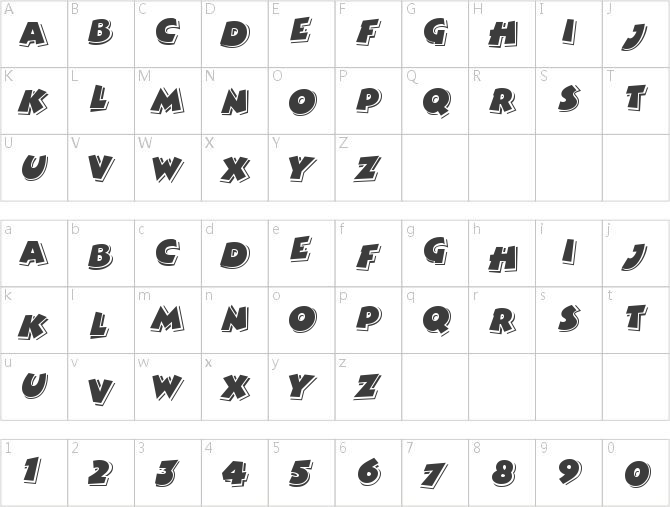
comixhighlightregular 詳情頁
comixhighlightregular字體字庫是一款讓人賞心悅目、百看不厭的英文字體,適合各類廣告和產(chǎn)品包裝設(shè)計應(yīng)用,字體大小0.06MB,格式為ttf字體,上傳用戶是順新廣告?,作者/版權(quán)方為未知